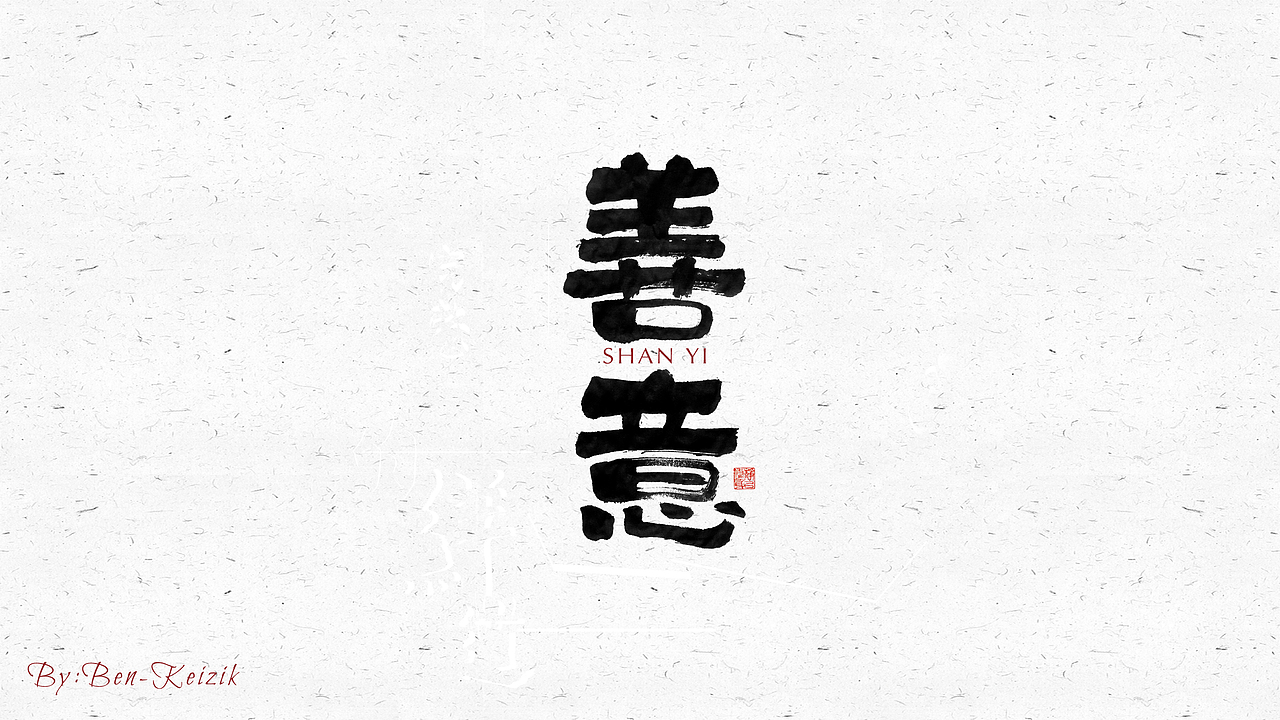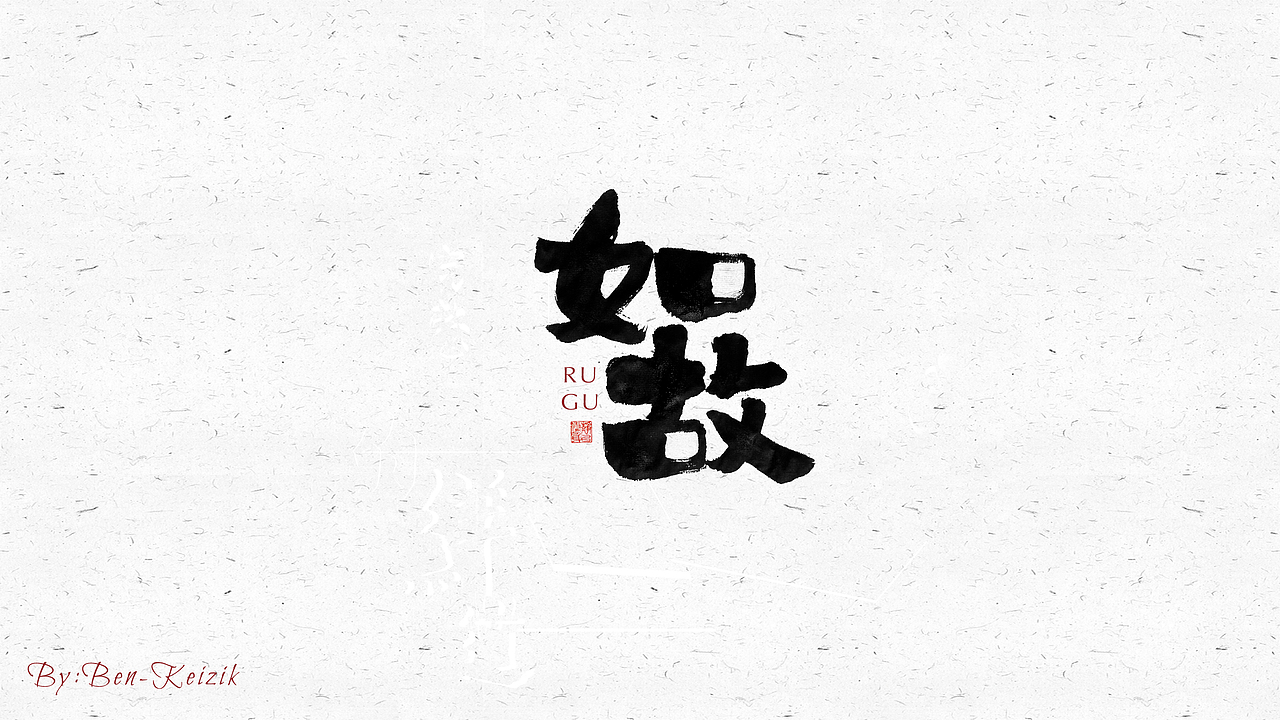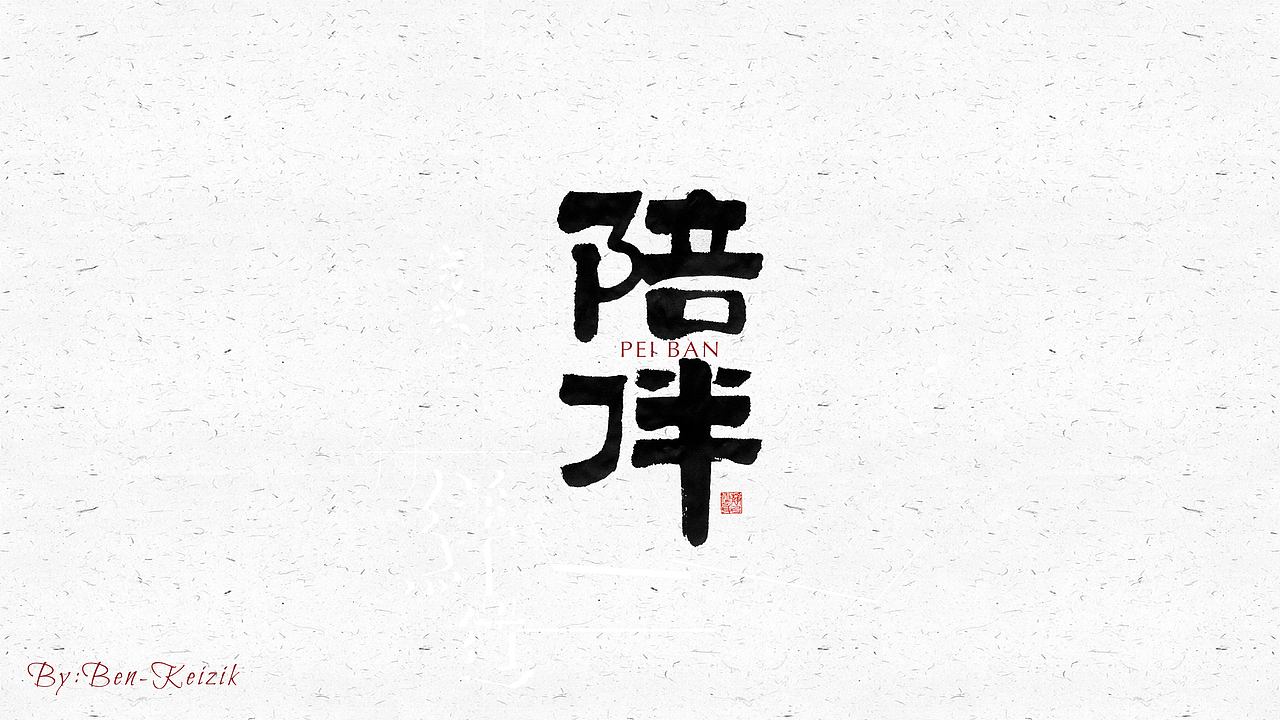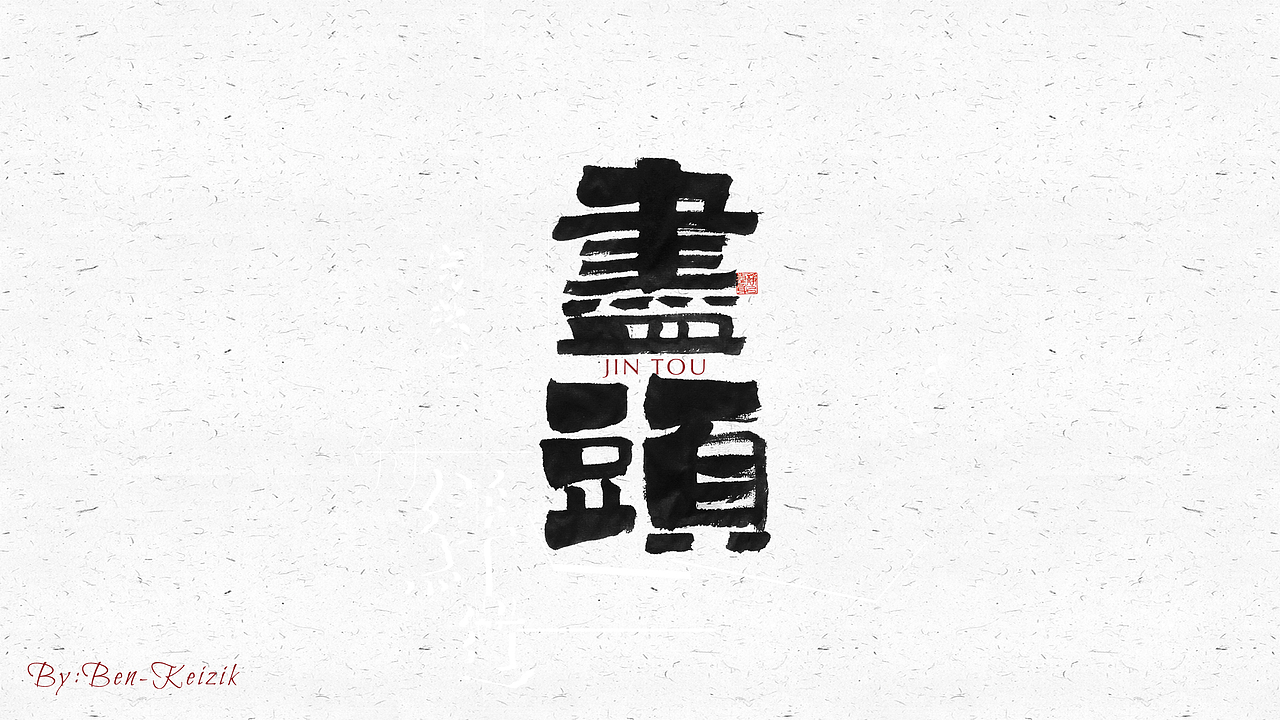
自言字语 —— 一组手写毛笔字(图ZMjI3MDY5NDgw) - 字体/字形 - 站酷设计师祺壹原创素材 - 站酷ZCOOL
自言字语 —— 一组手写毛笔字(图ZMjI3MDY5NDg4) - 字体/字形 - 站酷设计师祺壹原创素材 - 站酷ZCOOL
自言字语 —— 一组手写毛笔字(图ZMjI3MDY5NDE2) - 字体/字形 - 站酷设计师祺壹原创素材 - 站酷ZCOOL
自言字语 —— 一组手写毛笔字(图ZMjI3MDY5NDIw) - 字体/字形 - 站酷设计师祺壹原创素材 - 站酷ZCOOL
自言字语 —— 一组手写毛笔字(图ZMjI3MDY5NDI4) - 字体/字形 - 站酷设计师祺壹原创素材 - 站酷ZCOOL
自言字语 —— 一组手写毛笔字(图ZMjI3MDY5NDk2) - 字体/字形 - 站酷设计师祺壹原创素材 - 站酷ZCOOL
自言字语 —— 一组手写毛笔字(图ZMjI3MDY5NDU2) - 字体/字形 - 站酷设计师祺壹原创素材 - 站酷ZCOOL
自言字语 —— 一组手写毛笔字(图ZMjI3MDY5NDcy) - 字体/字形 - 站酷设计师祺壹原创素材 - 站酷ZCOOL
自言字语 —— 一组手写毛笔字(图ZMjI3MDY5NDY4) - 字体/字形 - 站酷设计师祺壹原创素材 - 站酷ZCOOL
自言字语 —— 一组手写毛笔字(图ZMjI3MDY5NDc2) - 字体/字形 - 站酷设计师祺壹原创素材 - 站酷ZCOOL
自言字语 —— 一组手写毛笔字(图ZMjI3MDY5NDI0) - 字体/字形 - 站酷设计师祺壹原创素材 - 站酷ZCOOL
自言字语 —— 一组手写毛笔字(图ZMjI3MDY5NTAw) - 字体/字形 - 站酷设计师祺壹原创素材 - 站酷ZCOOL
自言字语 —— 一组手写毛笔字(图ZMjI3MDY5NDM2) - 字体/字形 - 站酷设计师祺壹原创素材 - 站酷ZCOOL
自言字语 —— 一组手写毛笔字(图ZMjI3MDY5NDMy) - 字体/字形 - 站酷设计师祺壹原创素材 - 站酷ZCOOL
自言字语 —— 一组手写毛笔字(图ZMjI3MDY5NDQw) - 字体/字形 - 站酷设计师祺壹原创素材 - 站酷ZCOOL
自言字语 —— 一组手写毛笔字(图ZMjI3MDY5NDQ0) - 字体/字形 - 站酷设计师祺壹原创素材 - 站酷ZCOOL
自言字语 —— 一组手写毛笔字(图ZMjI3MDY5NDQ4) - 字体/字形 - 站酷设计师祺壹原创素材 - 站酷ZCOOL
自言字语 —— 一组手写毛笔字(图ZMjI3MDY5NDUy) - 字体/字形 - 站酷设计师祺壹原创素材 - 站酷ZCOOL
自言字语 —— 一组手写毛笔字(图ZMjI3MDY5NDYw) - 字体/字形 - 站酷设计师祺壹原创素材 - 站酷ZCOOL
自言字语 —— 一组手写毛笔字(图ZMjI3MDY5NDY0) - 字体/字形 - 站酷设计师祺壹原创素材 - 站酷ZCOOL
自言字语 —— 一组手写毛笔字(图ZMjI3MDY5NDg0) - 字体/字形 - 站酷设计师祺壹原创素材 - 站酷ZCOOL
自言字语 —— 一组手写毛笔字(图ZMjI3MDY5NDky) - 字体/字形 - 站酷设计师祺壹原创素材 - 站酷ZCOOL